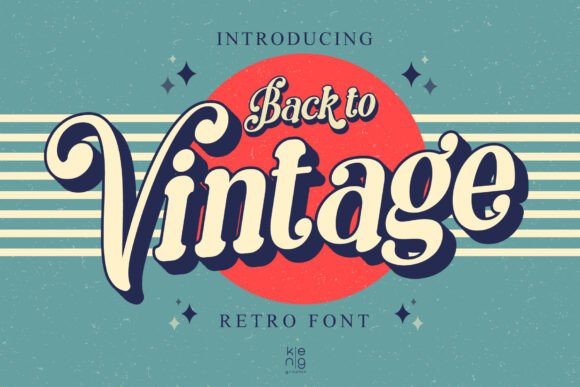
Back to Vintage
適切なデザイン要素を見つけるのは難しい場合がありますが、Back to Vintageは作品を即座に引き立てる優れたコレクションを提供します。
POD(オンデマンド印刷)製品、結婚式の招待状、またはソーシャルメディアのグラフィックを作成している場合でも、Back to Vintageは理想的です。